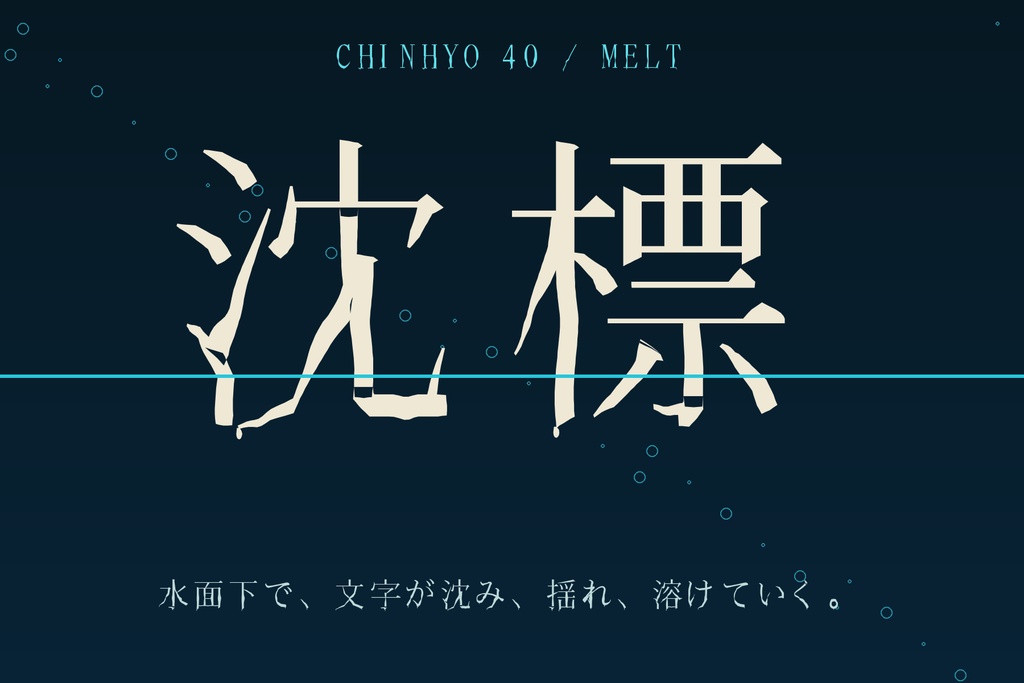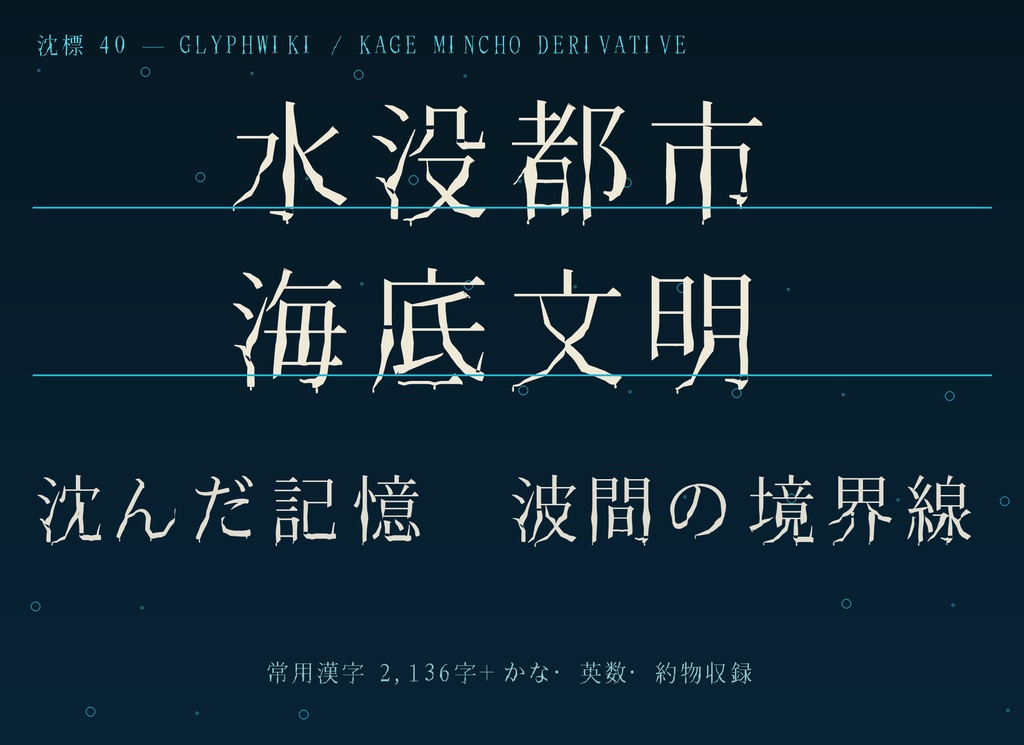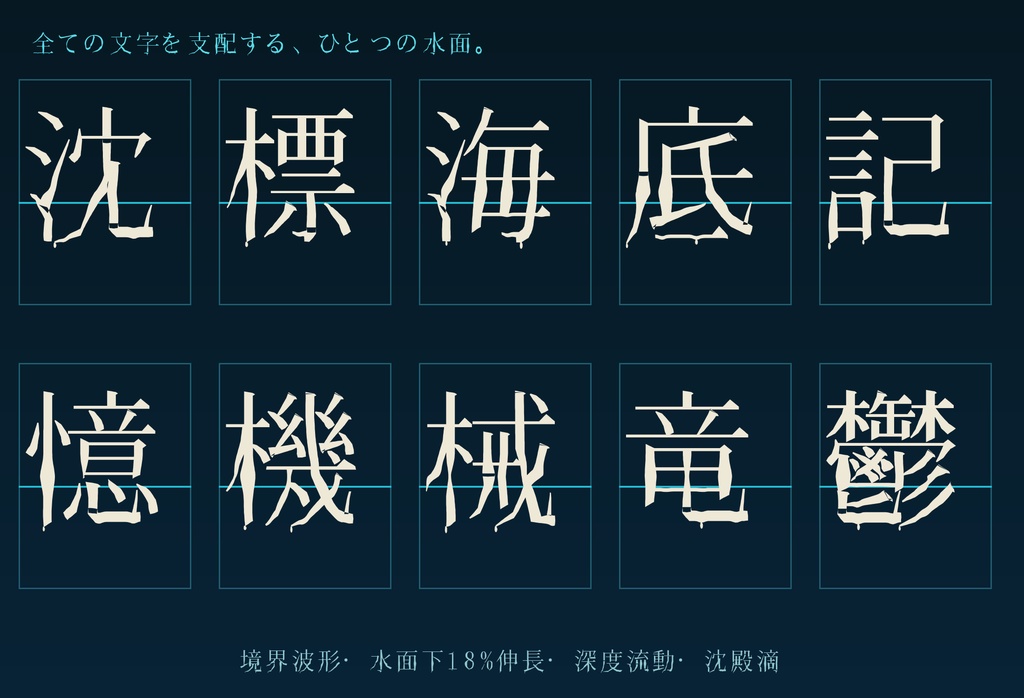
【沈標 / CHINHYO】水面下で溶ける日本語フォント|常用漢字2,136字収録
一文字の内部に水面を持ち、文字が沈み、揺れ、溶けていく日本語ディスプレイフォントです。 水面より上は乾いた明朝体、水面付近では輪郭が波打ち、水面下では線が太く引き延ばされ、端部に沈殿滴が溜まります。 「海」「沈」「底」だけの装飾ではなく、収録する全ての文字が同じ水中物理に従います。 ■ 特徴 ・文字高40%位置(下端基準)に共通水面 ・水面下18%伸長、深度に応じた横流れと溶解変形 ・文字ごとに異なる波の位相 ・常用漢字2,136字を全て収録 ・ひらがな、カタカナ、英数字、基本約物を収録 ■ 形式 TrueType(TTF) / Windows・macOS ■ 収録 2,541文字(空白を含む) 常用漢字:2,136字 ■ 利用 個人・商用利用可。ロゴ、動画、ゲーム、印刷、配信、同人・商業作品に使用できます。クレジット不要。 フォントデータの再配布・共有・転売は禁止です。詳細はZIP内の利用規約をご確認ください。 ※見出し・タイトル向けの装飾書体です。小サイズの本文用途には向きません。